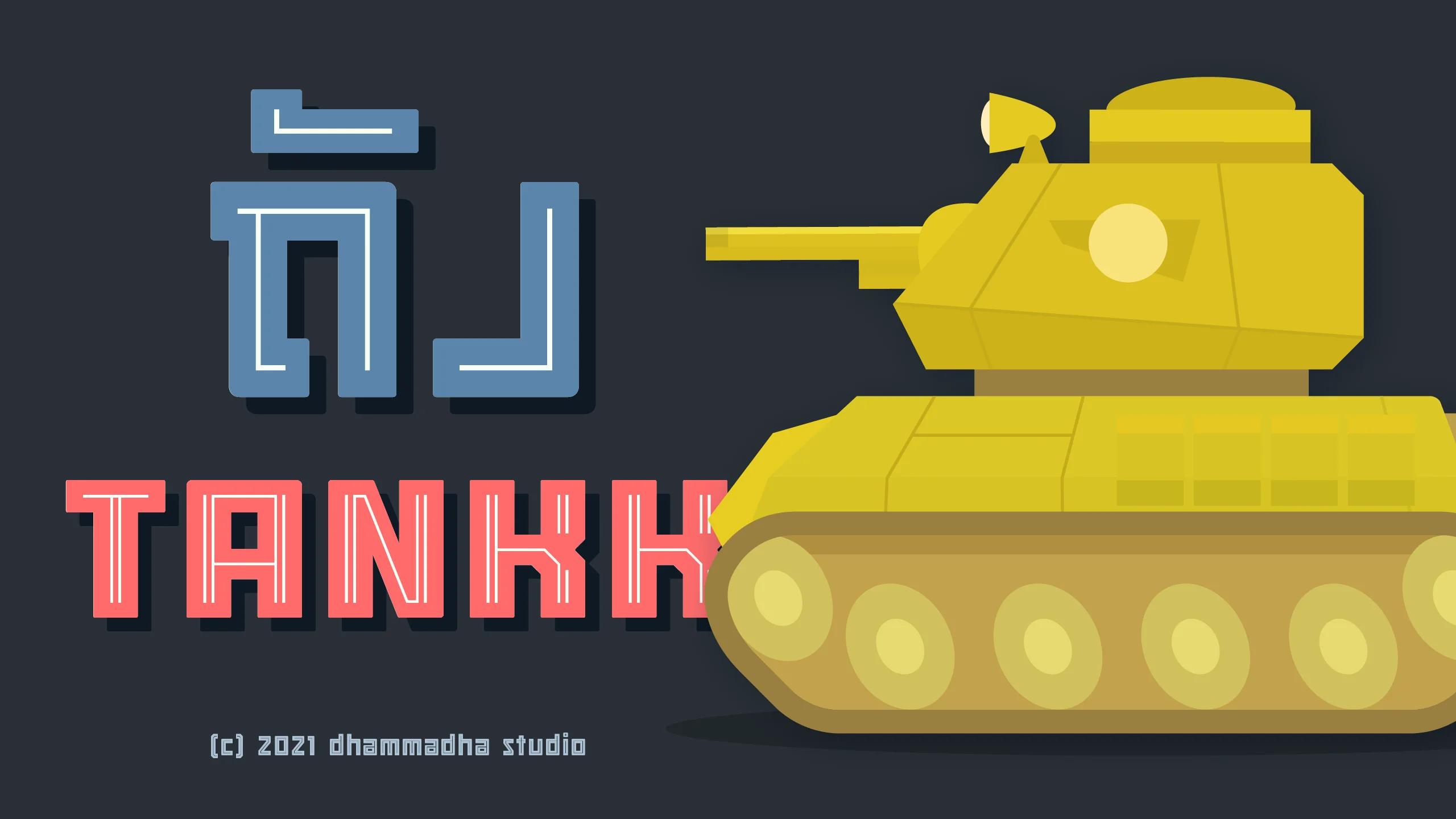
ชุดอักษรที่พาคุณย้อนเวลากลับไปสัมผัสความทรงจำในวัยเยาว์ผ่านรูปลักษณ์ที่ดูเข้มแข็งและบึกบึน เราตั้งใจออกแบบให้ตัวอักษรแต่ละตัวมีน้ำหนักที่เต็มเปี่ยมไปด้วยพลัง สะท้อนถึงความแข็งแกร่งและความหนักแน่นอย่างตรงไปตรงมา ด้วยโครงสร้างที่ดูบึกบึนเป็นพิเศษทำให้ฟอนต์ชุดนี้มีเอกลักษณ์เฉพาะตัวที่ไม่ซ้ำใคร มอบบรรยากาศที่ดูจริงจังแต่แฝงไว้ด้วยความสนุกสนานแบบย้อนยุคที่ชวนให้คิดถึง ด้วยบุคลิกที่เน้นความทรงพลัง "ถัง | TANKK" จึงถูกสร้างมาเพื่อทำหน้าที่เป็นฟอนต์พาดหัว (Display Font) ที่พร้อมจะกระแทกสายตาผู้พบเห็นในทันที เหมาะอย่างยิ่งสำหรับงานออกแบบที่ต้องการความโดดเด่นขั้นสุด ไม่ว่าจะเป็นป้ายโฆษณา งานกราฟิกสายลุย หรือคอนเทนต์ที่ต้องการความชัดเจนและมีพลัง พิเศษ !! ชุดฟอนต์ TANKK SOLID อำนวยความสะดวก เมื่อต้องการไฮไลท์เส้น Inline แถมฟรี !! เมื่อสั่งซื้อ TANKK FULL FAMILY